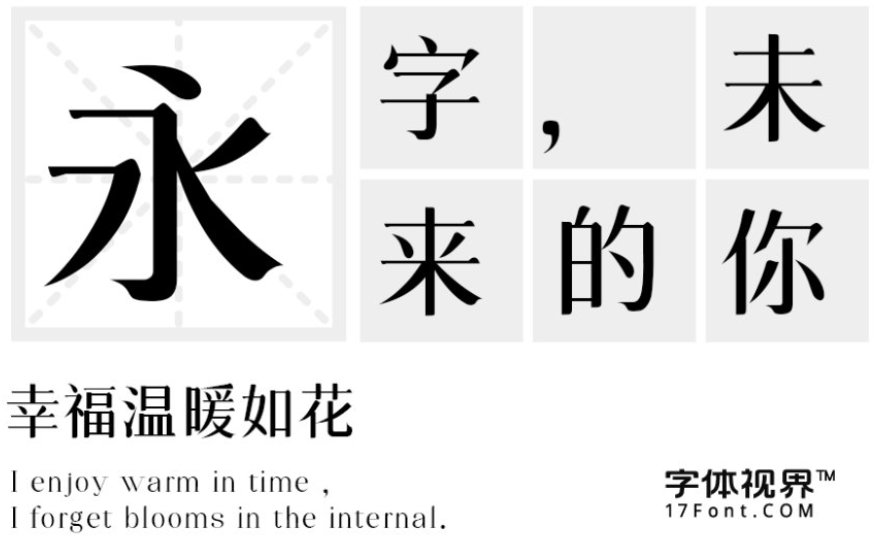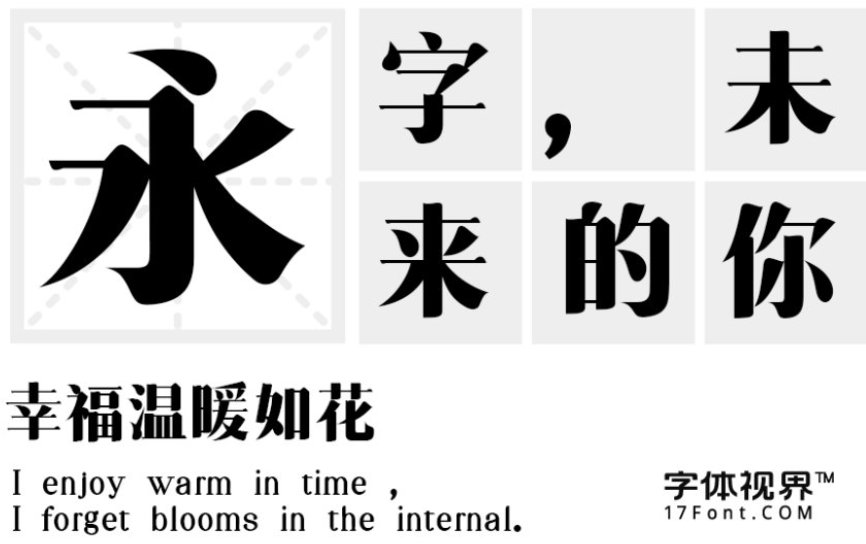
三极柔宋简体发布
字体名称:三极柔宋简体
字体类别: 宋体
适用场景:广告、标题、印刷
三极柔宋简体简介:三极柔宋简体是一款适合手写艺术设计的字体,是一款家族字体,其字形清新,布白均匀,字形结构饱满匀称、柔美,中宫偏大,笔形挺拔流畅,笔锋锐利简洁。撇、捺起笔收笔统一,个性鲜明,富有朝气。这款字的整体风格清新醒目、时尚柔美,精致富有内涵。横竖笔画的粗细反差较大,具有强烈的视觉冲击力。
三极柔宋简体预览图展示:
系列字体之三极粗柔宋简体展示: